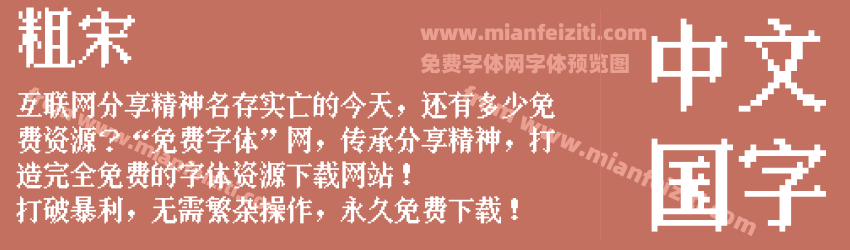
粗宋
字体风格: 宋体
大家好,这是我在itch.io的第一个项目。这是我做的字体粗宋,我是依据《如何将点阵汉字矢量化》这篇文章进行操作而成(但我用的是bdfresize而不是该死的potrace.sh)(24px不在这里)。
点阵字体(Dot Matrix Fonts,也叫 Bitmap Fonts)的使用已经是很久之前的事情,目前公认的最早的点阵字体出现在世界上第一台全电子自动排字机上,它就是 1966 年德国发明家 Dr. Ing. Rudolf Hell 发明的 Hell 50T1 Digiset。
而中文点阵字体的使用也有几十年了,那时候比较流行软/硬汉字系统(看你是否知道 CCDOS,UCDOS,213 什么的?),常用到 16 和 24 点阵的汉字。由于以前屏幕的分辨率比较低,点阵汉字还是相当的够用。后来,随着图形化操作系统的普及,矢量字体(Outline Fonts, Vector Fonts)大行其道,其矢量渲染的方式能够显示出平滑的字体,体验大大超过了传统的点阵字体,理所当然的成为了当前的主流。
那么是不是点阵汉字就已经退出历史舞台了呢?并没有。现在街上能常常见到的简易 LED 屏,很多都还是用的点阵汉字。很多工控或者简易屏幕上,也都还在使用点阵汉字,这是因为同矢量字体相比,点阵汉字占用的空间极小,这是由于点阵汉字的特性所决定的
本款“粗宋”是一款书写很新颖的字体,字体大方,适合各种设计作品使用!欢迎下载!